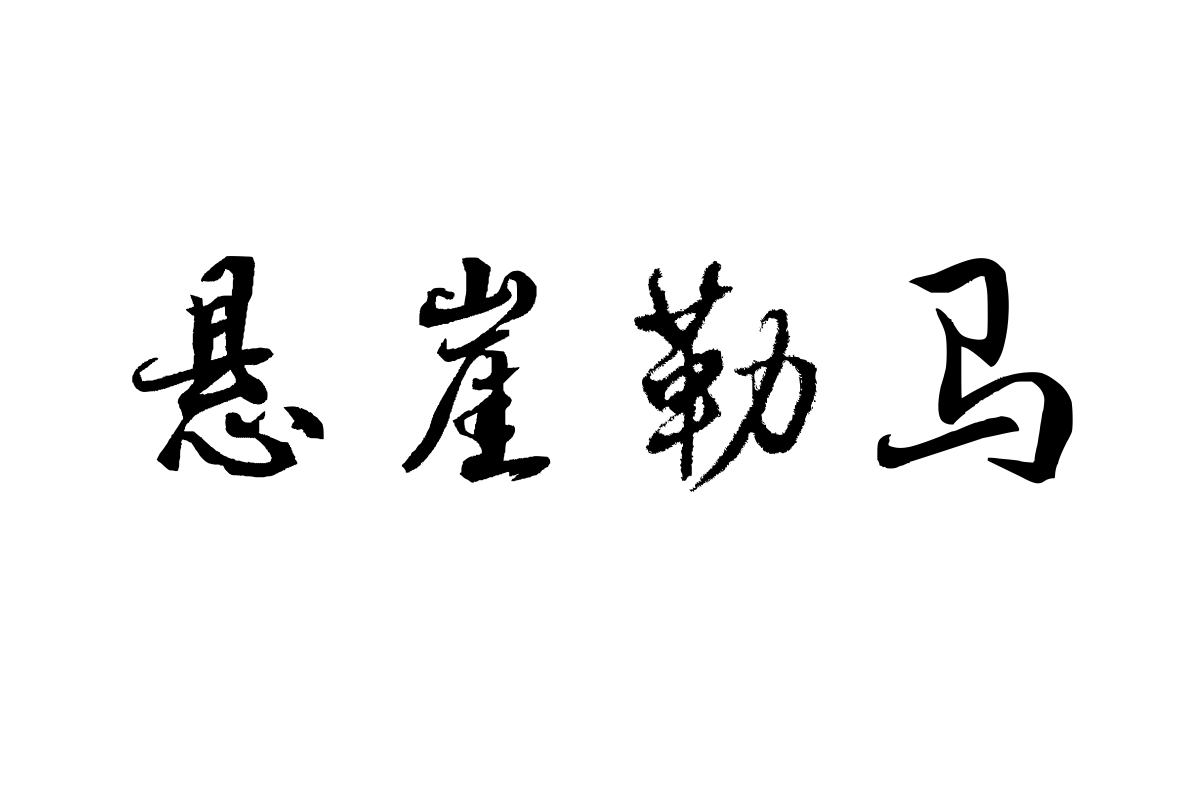
汉呈王久存行书字体是一种书法艺术风格,源自中国古代的书法传统。这种字体的特点是笔画流畅,字形优美,结构严谨,具有很高的艺术价值和观赏价值。
汉呈王久存行书字体的特点如下:
1. 笔画流畅:汉呈王久存行书字体的笔画线条流畅自然,没有过多的顿挫和转折,给人一种优雅、和谐的感觉。
2. 字形优美:汉呈王久存行书字体的字形结构紧凑,线条粗细适中,既有力度又不失柔美,给人以美感。
3. 结构严谨:汉呈王久存行书字体的结构布局严谨,每个字都经过精心设计,使得整个作品呈现出一种统一和谐的效果。
4. 艺术价值高:汉呈王久存行书字体是中国古代书法艺术的代表之一,具有较高的艺术价值,是研究中国古代书法文化的重要资料。
5. 观赏性强:汉呈王久存行书字体的字体大小、形状、颜色等都可以根据需要进行设计,具有很强的观赏性和实用性。
总之,汉呈王久存行书字体是一种具有很高艺术价值和观赏价值的书法艺术风格,深受人们的喜爱和推崇。